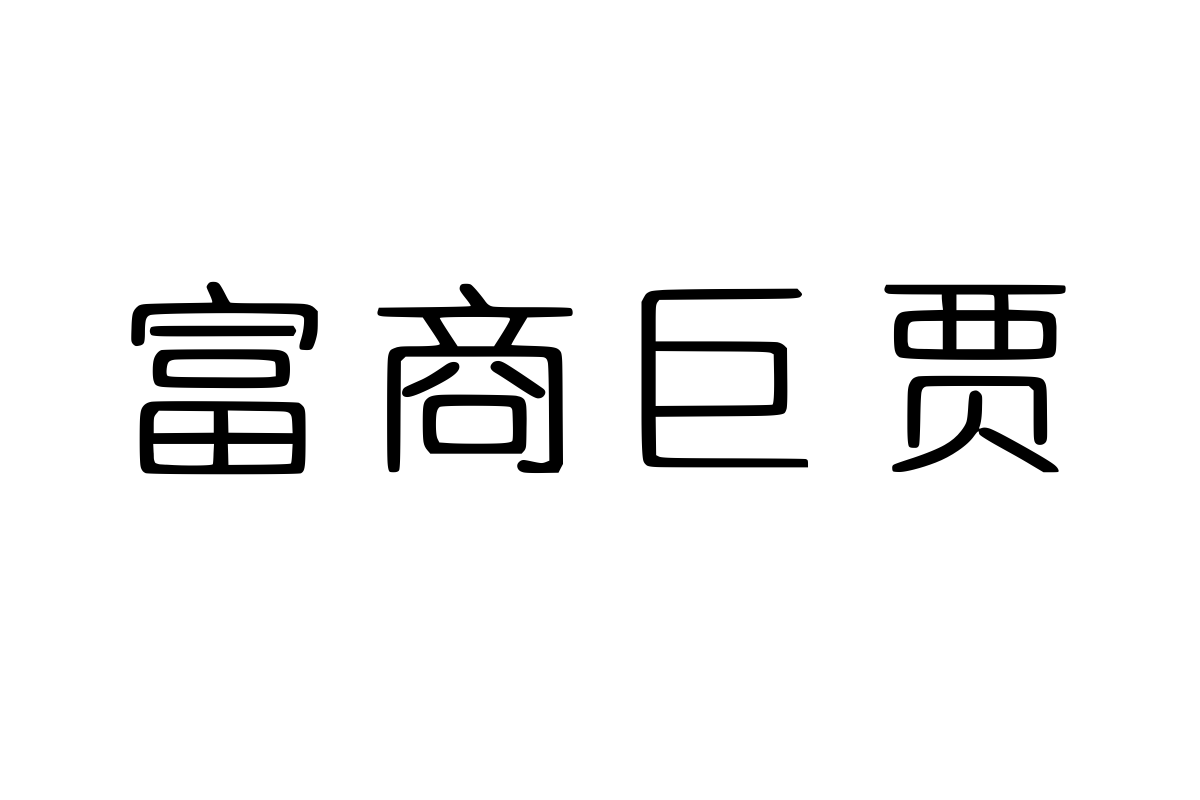
兰米黑圆体(Rammi Black Round)是一款由日本字体设计师田中一郎设计的无衬线字体。这款字体以其简洁、现代的风格而受到广泛欢迎,广泛应用于各种商业和专业用途。
兰米黑圆体的特点如下:
1. 无衬线设计:这款字体采用了无衬线设计,使其具有现代感和清晰易读的特点。这种设计使得文字在视觉上更加简洁,易于阅读和识别。
2. 粗细均匀:兰米黑圆体在粗细上的过渡非常自然,没有明显的断点或突兀的感觉。这使得文字在不同大小和距离下都能保持良好的可读性。
3. 多种字重:兰米黑圆体提供了多种字重,包括常规字重、粗体字重和特大字重。这些不同的字重可以满足不同场景的需求,如标题、正文和强调等。
4. 适用范围广泛:兰米黑圆体适用于各种商业和专业用途,如广告、标志、包装、网站和印刷品等。它不仅适合正式场合,也适合创意和个性化的设计。
5. 支持多语言:兰米黑圆体支持多种语言的输入和显示,包括日语、韩语、英语等多种语言。这使得它在国际化的应用中更具优势。
总之,兰米黑圆体是一款简洁、现代且功能强大的无衬线字体,适用于各种商业和专业用途。